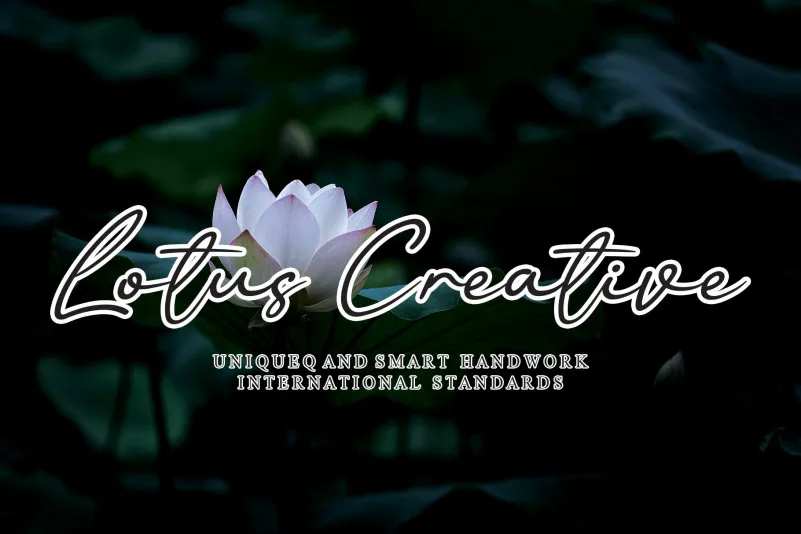
Lotus Creative Script Font – Download Grátis
A Lotô Script Font é uma elegante fonte escrita a mão que proporciona um toque sofisticado e limpo. Seu fluxo gracioso e seu charme distendido tornam-se irresistíveis, tornando-a uma escolha preferencial para qualquer projeto em pouco tempo. Com este estilo único e profissional, ela se destaca entre as muitas fontes escritas a mão disponíveis no mercado. A designer andikastudio criou essa fonte com um cuidado notável, mantendo os detalhes de escrita em alta resolução. E embora seja uma fonte escrita a mão, sua aparência elegante faz dela perfeitamente adequada para textos legíveis e profissionais. Esta é uma ótima escolha para quem procura algo além das fontes digitais mais comuns e quer uma fonte que represente suas ideias de maneira única e sofisticada. Sem dúvida, a Lotô Script Font será um elemento chave no seu próximo projeto gráfico.